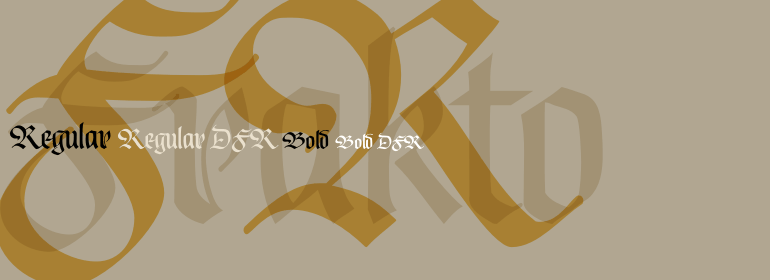
Frakto™
Frakto™,这款字体结构工整、笔画清晰,兼顾美观与易读性,适用于标题、正文、海报、包装、LOGO 等多种场景。字形优雅稳定,风格百搭耐看,适配日常排版与创意设计,让文字呈现更舒适、更具质感。Frakto™一笔一画,皆是细节,以均衡的比例、流畅的线条打造舒适视觉体验,字形端正大气,风格简约现代。无论是商业设计、品牌宣传还是日常排版,都能轻松驾驭,让文字更有格调与力量。Frakto™字体下载。
字体品牌: Linotype(Monotype) 设计师:Goede,Julius de 字体分类:衬线体 字体属性:外文 字符集:Unicode 发布时间: 2018